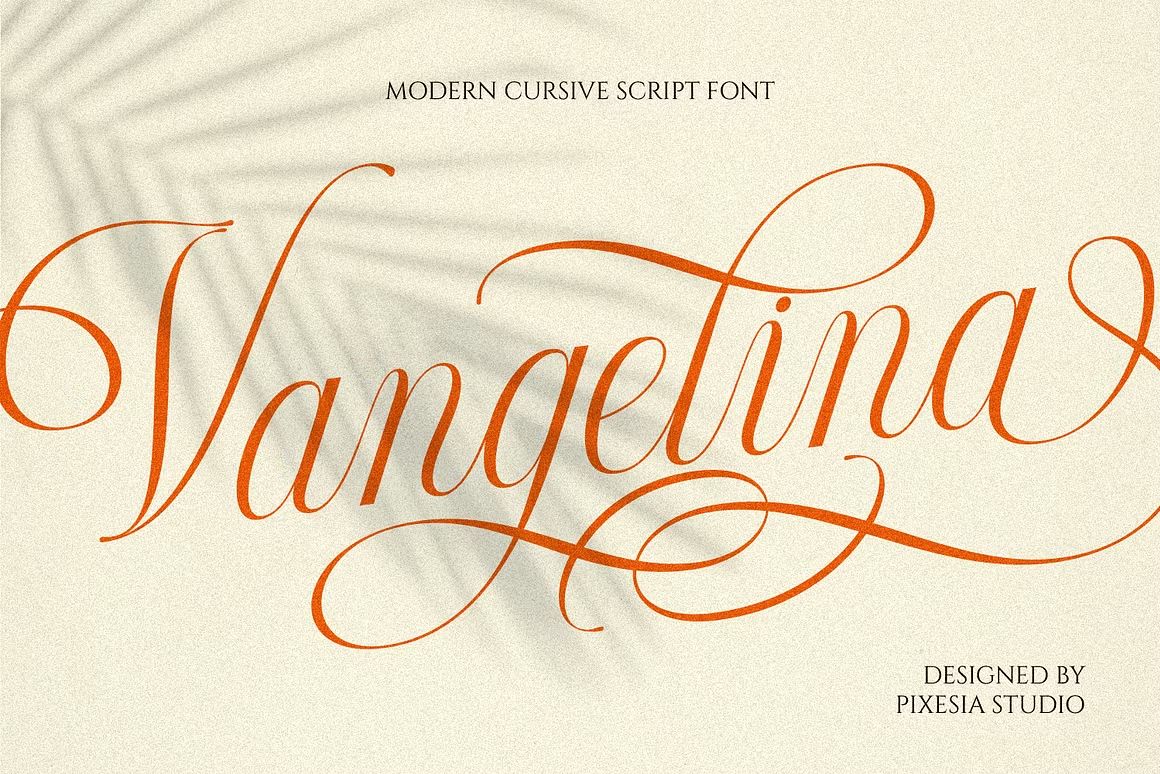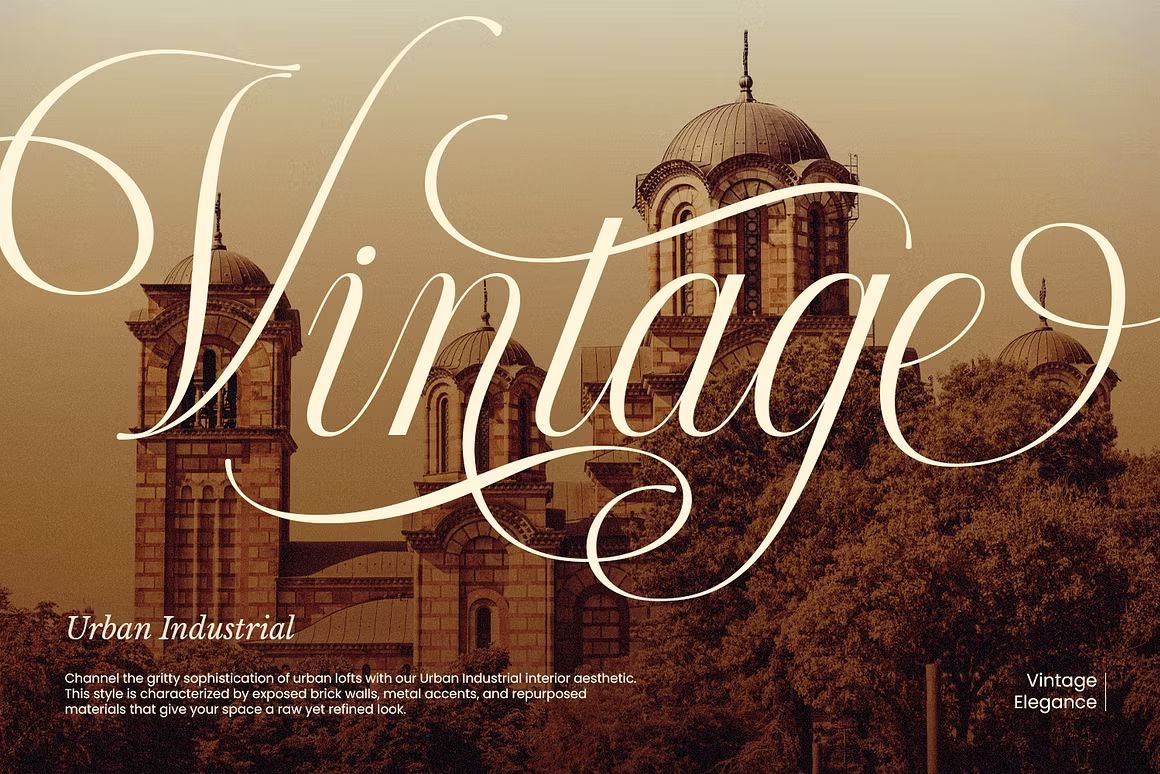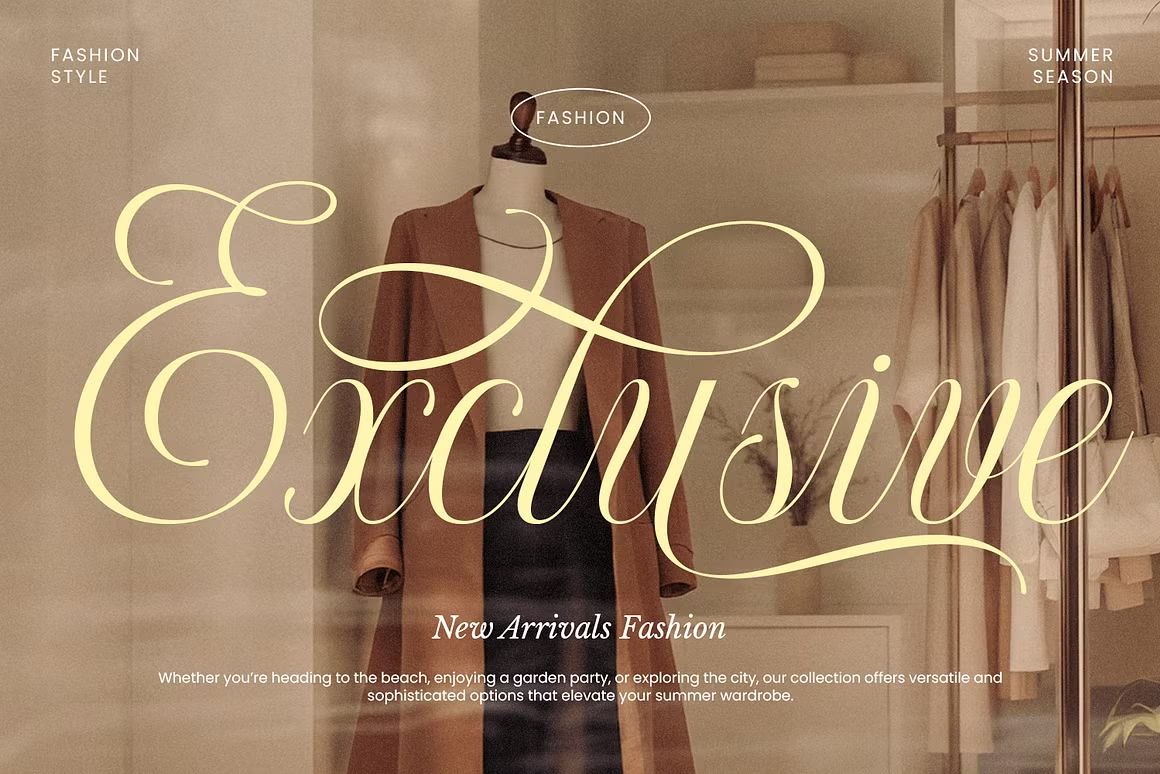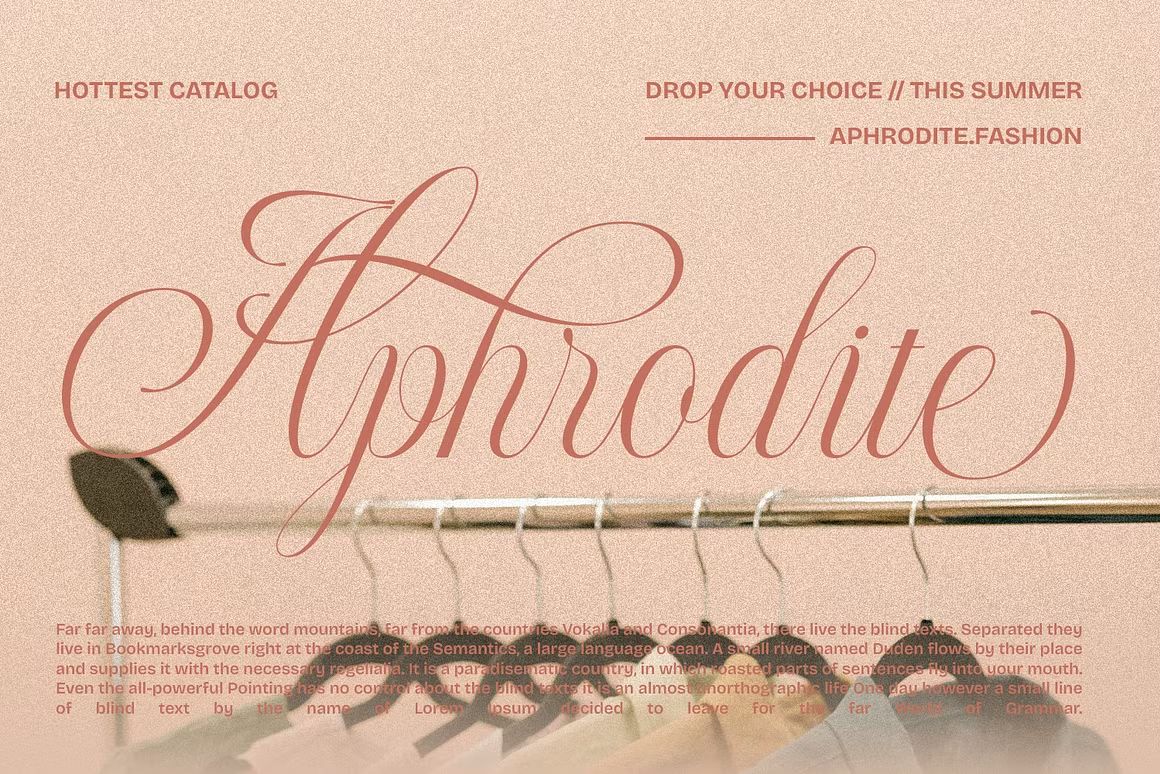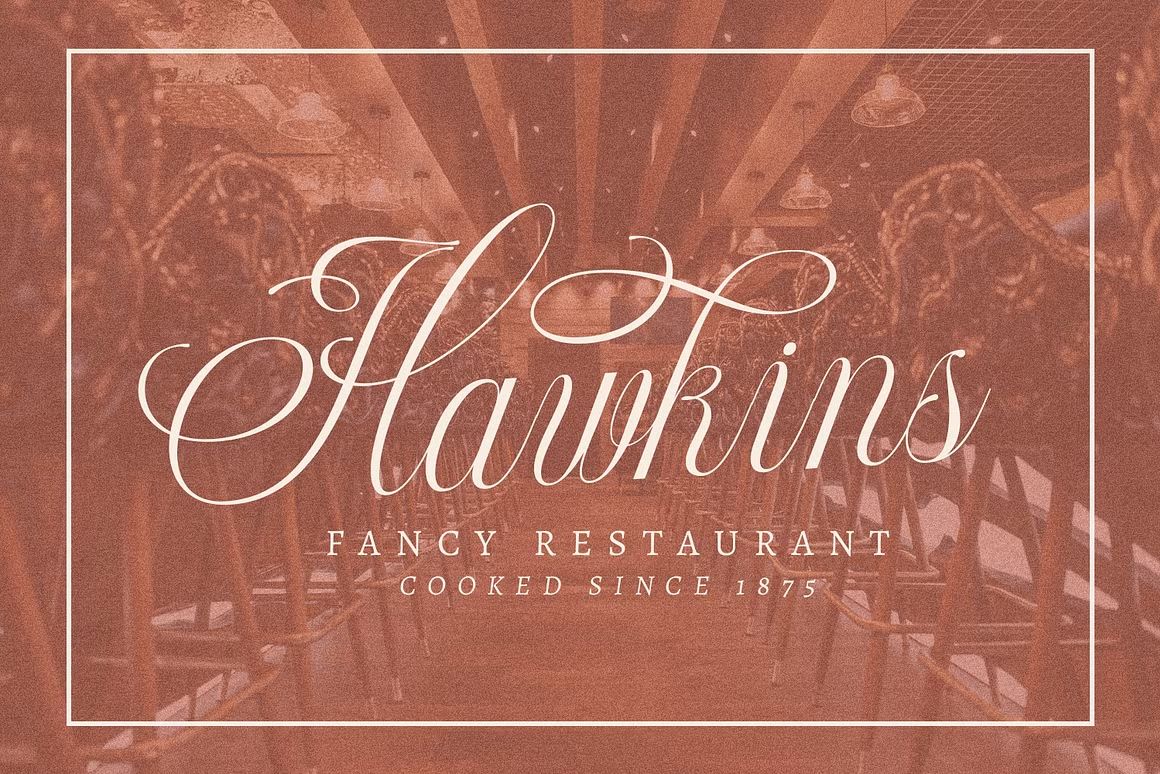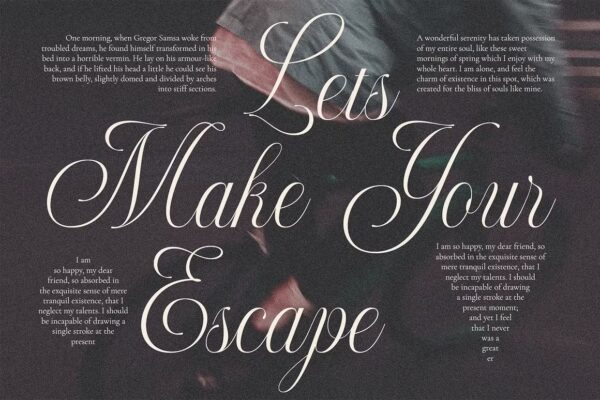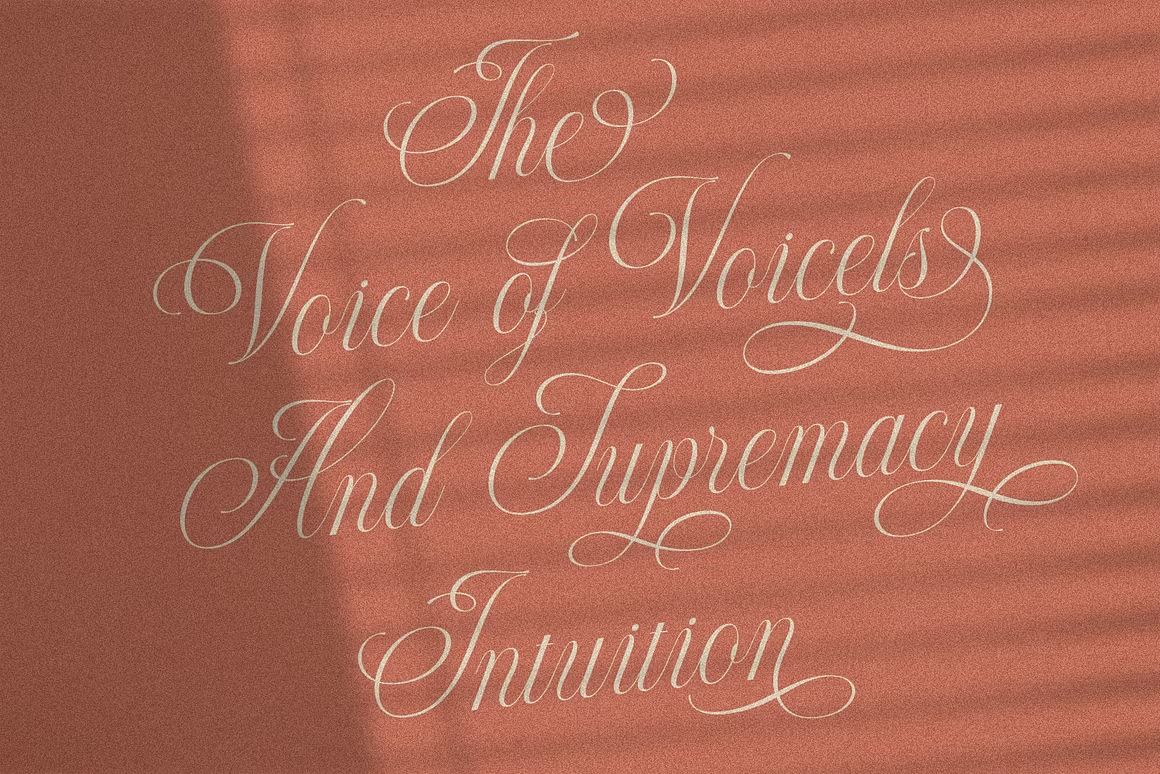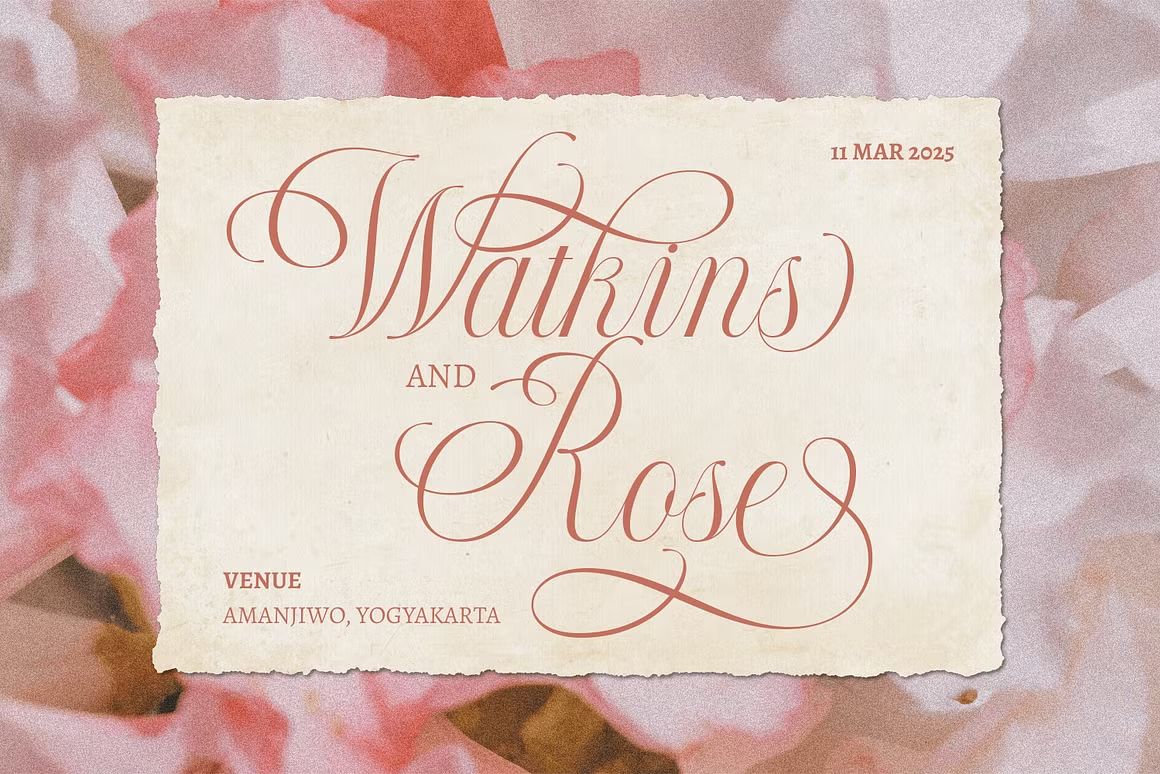
Vangelina – Script Font
Vangelina adalah font script elegan dan feminin, cocok untuk wedding, branding, dan desain estetik. Format OTF/TTF/WOFF, siap digunakan.
Vangelina adalah font script bergaya elegan dengan alur tulisan tangan yang halus dan feminin. Cocok untuk berbagai proyek seperti undangan pernikahan, logo brand kecantikan, kutipan estetik, kemasan mewah, dan media sosial. Dengan karakter yang anggun dan detail yang rapi, Vangelina memberikan kesan romantis, modern, dan profesional.
• Script font dengan gaya elegan dan feminin
• Ideal untuk wedding, branding kecantikan, dan desain estetik
• Termasuk huruf besar, kecil, angka, simbol, dan ligatur